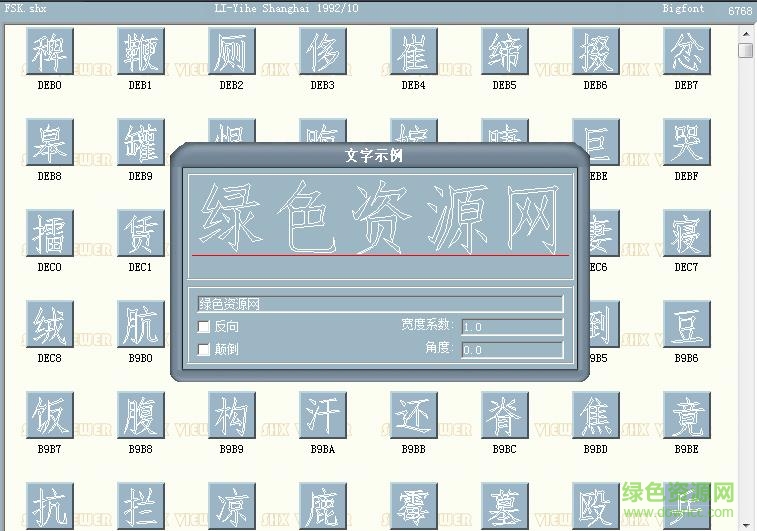
fsk.shx字體的樣式在如今眾多的字體中都不常見(jiàn),是一款十分稀有的字體文件,通過(guò)將用戶(hù)所需的制圖字符以及字體進(jìn)行.shx字體制作,讓你能夠隨時(shí)在cad軟件中進(jìn)行調(diào)用!
fsk.shx的風(fēng)格十分有趣,是一款中心鏤空的字體,用戶(hù)在使用的時(shí)候即能夠感受到鏗鏘有力的字體結(jié)構(gòu),也能夠獲得鏤空字體體驗(yàn),十分不錯(cuò)!
2、SHX形字體屬于”矢量字型,是一種用形狀或方程來(lái)描述字符輪廓的字符形式。這種字型的優(yōu)點(diǎn)是在顯示時(shí)字符可以任意縮小放大,缺點(diǎn)是需要做大量的處理。